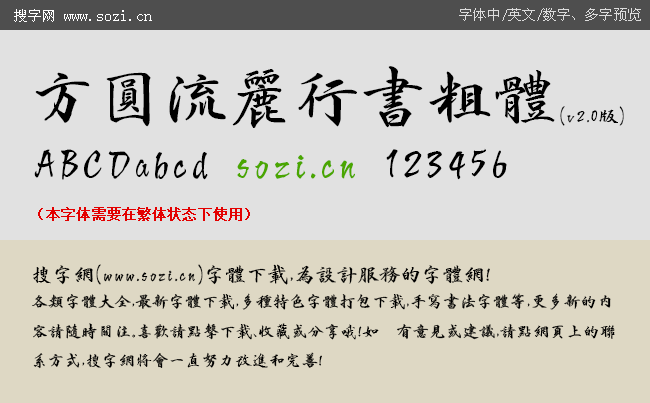
方圓流麗行書(shū)粗體
搜字網(wǎng)提供一款方圓流麗行書(shū)粗體中文字體下載, 方圓流麗行書(shū)是一款非常漂亮的手寫(xiě)風(fēng)格行書(shū)書(shū)法字體,字體筆畫(huà)鋒利,棱角分明,可適用于繪畫(huà)設(shè)計(jì)、廣告設(shè)計(jì)、平面設(shè)計(jì)、個(gè)性簽名等領(lǐng)域。